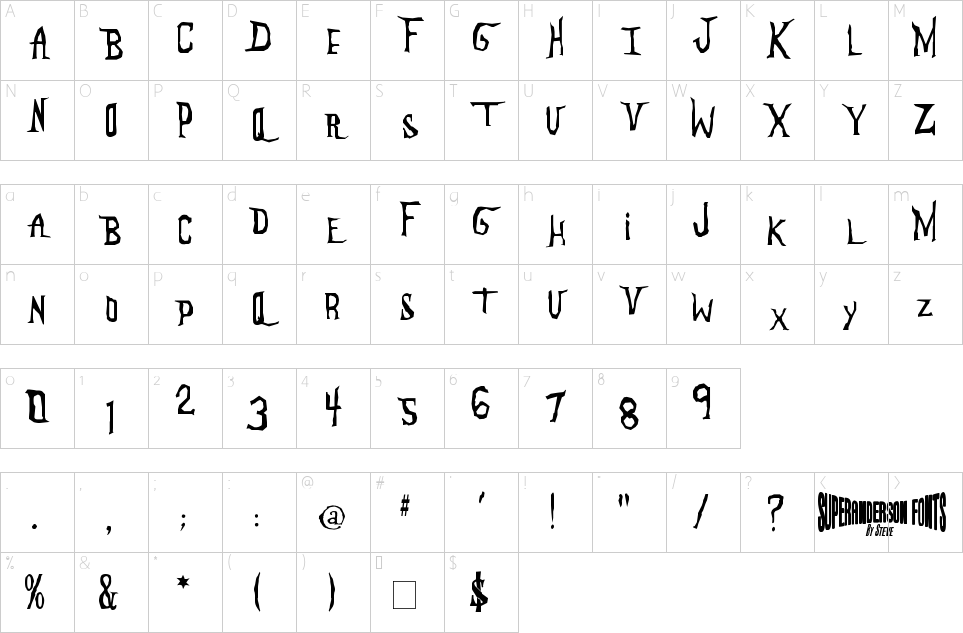
A fonte “Anderson The Mysteron” é uma criação do designer Steve Ferrera, disponível gratuitamente tanto para sistemas Windows quanto para Mac. Esta fonte adota um estilo único e criativo, caracterizado por linhas elegantes e detalhes únicos que trazem ao seu design uma certa elegância e sofisticação. Com ela, você pode adicionar um toque único e emocionante a seus projetos digitais. Com seu uso, suas criações ganham um brilho especial, destacando-se em meio a outros projetos. A fonte “Anderson The Mysteron” está disponível para download em sua versão gratuita, oferecendo a você uma maneira prática de incorporar um elemento inovador em seu trabalho. Com mais de 14 mil downloads, o público já testemunhou a qualidade desta fonte e está de olho em sua versão gratuita para experimentar as inúmeras possibilidades que ela apresenta.